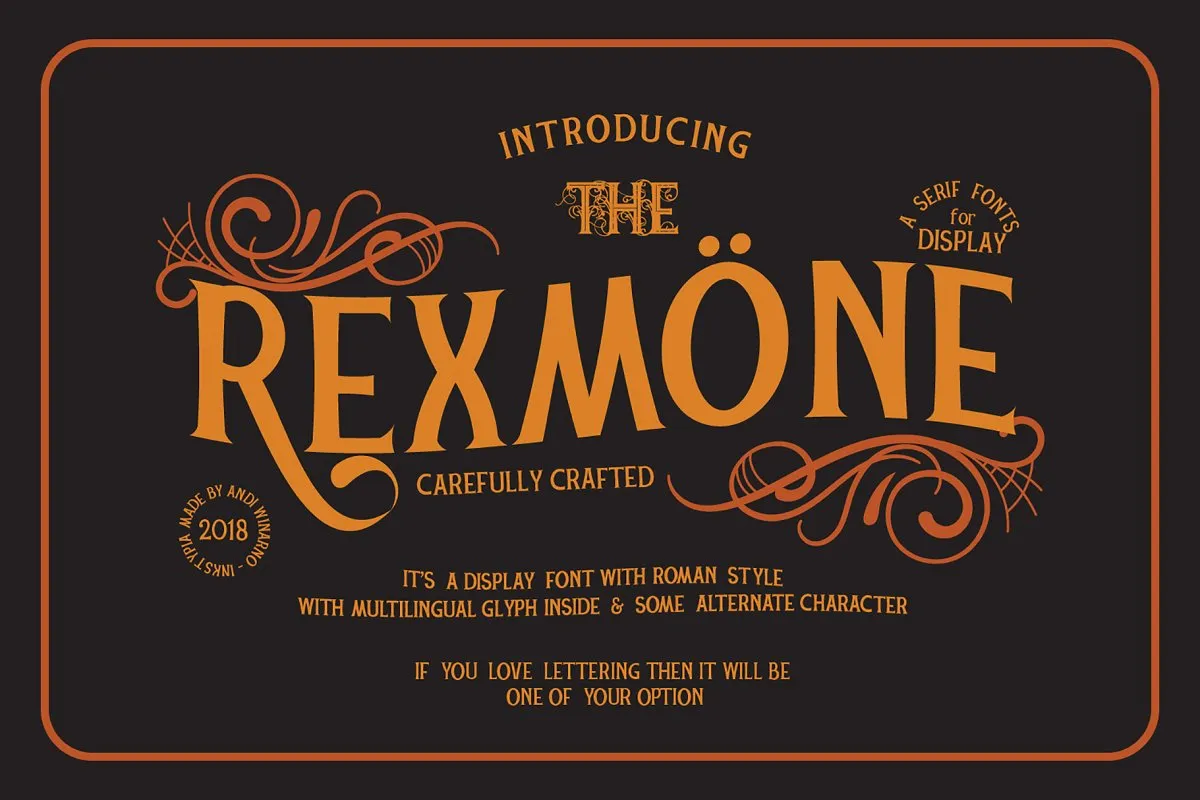
A REXMONE Typeface é uma nova serif tipo com estilo romano que traz à tona uma opção agradável para projetos design que exigem elegância e sofisticação. Ela foi criada por INKsTYPIA e agora pode ser encontrada em formatos True Type e Opentype, oferecendo muitas línguas e caracteres alternativos. Se você está buscando uma fonte versátil para trabalhos como logotipos, cartazes, letras, ou rótulos, a REXMONE é uma ótima opção que adicionará um toque diferenciado ao seu trabalho. Com sua simplicidade e elegância, ela pode ser usada em diversas aplicações onde desejar fazer o design mais sofisticado. Seja para criar um logotipo memorável ou imprimir um rótulo de produto, a REXMONE Typeface é uma fonte que merece atenção.